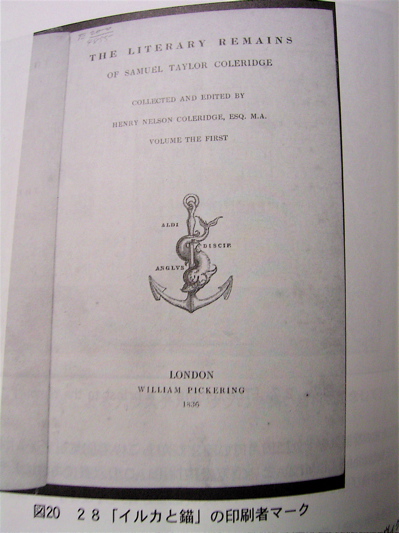
東大の総合図書館
昨日まで東大の総合図書館で、東大創立130周年・総合図書館再建80周年を記念した展示会「世界から贈られた図書を受け継いで」が開催されていました。
私がお目当てだったのは、モリスのケルムスコットプレスの「チョーサー著作集」や、「The temple & priest to the temple」、それからボドニーの書体で印刷されたページでした。ボドニー書体のページには「まさにオリジナルのボドニーの雄姿」と説明書きにありました。活字の雄姿です!
「Festina Lente」(急いでゆっくり)という銘文が入っています。これは、アルドゥス・マヌティウス(15世紀に活躍した、商業印刷父と言われるルネサンス期ヴェネツィアの出版人)が最初に用いたことで有名だそうです。
早さに力点をおいて「イルカ」を、その早さを抑える象徴として船の「錨」を意味しているのだそうです。
他にはモースの「日本その日その日」という本の電鋳板が出ていました。
電鋳板ってなんでしょう??
電鋳板とは活字組をしたページを電気的に複製して作った印刷版のこと、だそうです。
電気的な複製って一体なんでしょう??ますます謎ですね。でも文字も挿絵も一体になった鉛の板の版のようでした。